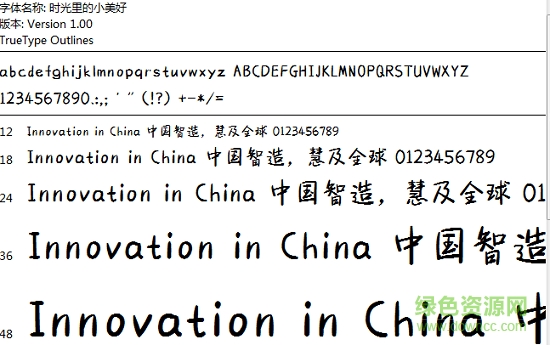
qq時光里的小美好字體是一款非常好看的中文手寫字體,這款字在有些地方的連筆處理顯得非常的生動,將一款比較正式的字體瞬間變得活潑、靈動,感興趣歡迎下載!
qq時光里的小美好字體是qq中一款非常好看的字體,這款字體是方正專為手機(jī)用戶打造的,采用手寫風(fēng)格,并且融入黑體字體的特色,使得效果變得明顯!